Tipo de letras bonitas#𝟙😎💋꧁༺?�༒♛𝓣𝓲𝓹𝓸𝓼 𝓓𝓮 𝓛𝓮𝓽𝓻𝓪𝓼 ♛༒?�༻꧂ Tipografías (Copiar y Pegar) Generar Diferentes Tipografías
El tipo de letras con estilo decorativo permite transformar frases simples en mensajes visualmente atractivos. Muchas personas buscan tipos de letras bonitas para dar un toque especial a nombres, estados o mensajes cortos creados con ChatGPT. Estos estilos ayudan a captar atención de forma inmediata y hacen que el texto se sienta más personal, cercano y expresivo en cualquier entorno digital.
¿Cuáles son los tipos de letras?
Letras Bonitas Únicas
El tipo de letras con diseños únicos aporta originalidad. Muchas personas buscan tipos de letras nombres para personalizar perfiles o firmas digitales. Estos estilos no siguen reglas tradicionales y combinan símbolos con caracteres especiales, logrando resultados llamativos que destacan frente a textos comunes y generan una impresión visual memorable. Son especialmente populares entre los jugadores de títulos como PVZ Fusion, donde un apodo con estilo puede hacer que el perfil sea más distintivo.
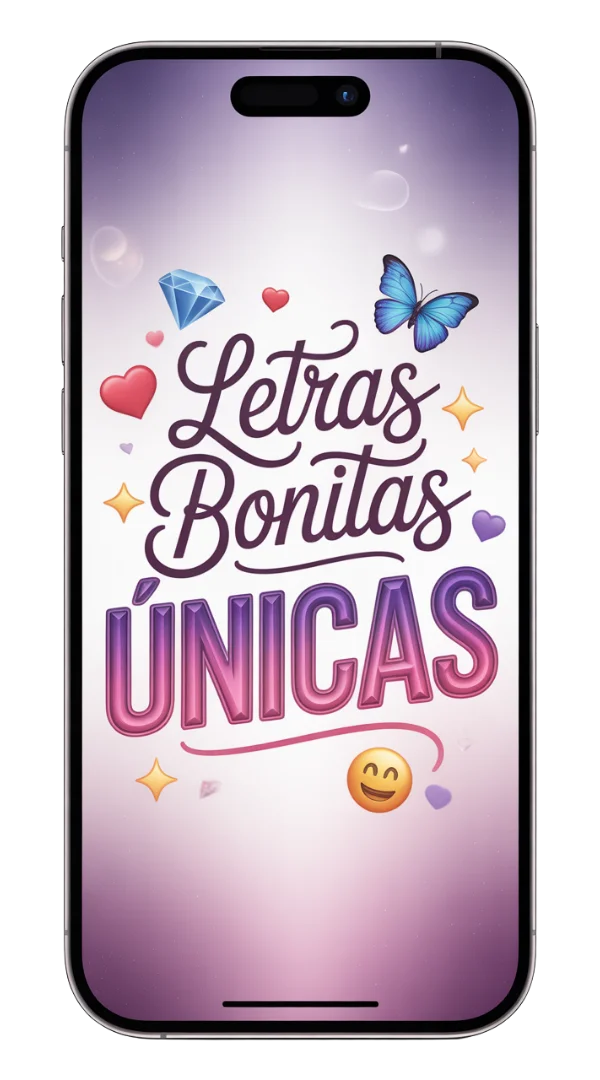
Texto Elegante
Un tipo de letras elegante transmite sobriedad y buen gusto. Entre los diferentes tipos de letras, este estilo es ideal para mensajes formales o presentaciones personales. Su apariencia limpia y estilizada ayuda a comunicar seriedad sin perder atractivo visual, siendo una opción muy valorada en contextos digitales profesionales.
Letras Cuadradas
El tipo de letras cuadrado se caracteriza por formas firmes y definidas. Muchos usuarios buscan tipo de letras diferentes para lograr un aspecto moderno y estructurado. Este estilo transmite orden y fuerza visual, lo que lo hace perfecto para títulos, nombres cortos o mensajes que necesitan impacto inmediato.
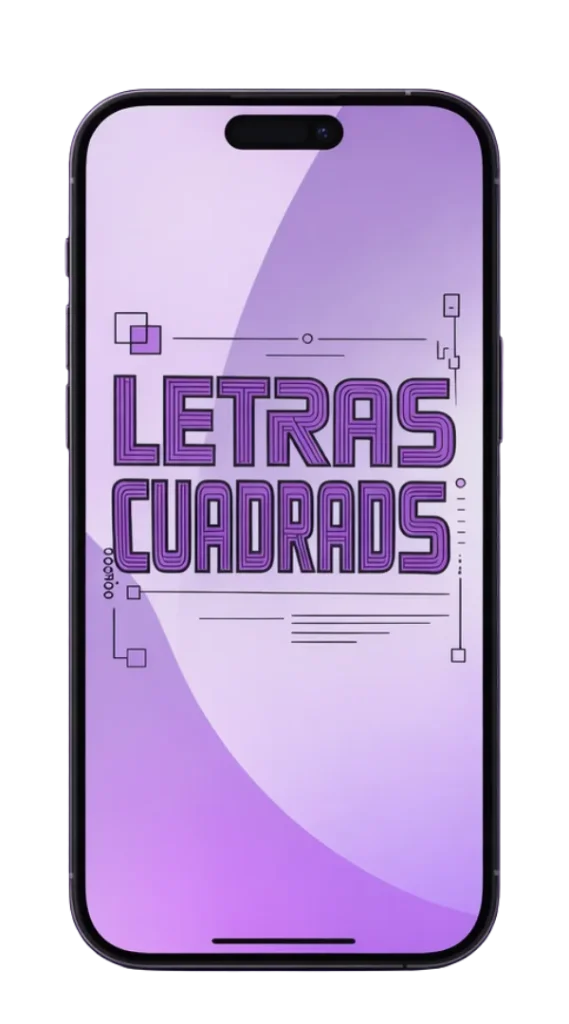
Escribe o pega tu texto
En el primer cuadro, introduce el texto que deseas transformar. Puedes escribir una palabra, una frase o un nombre completo.
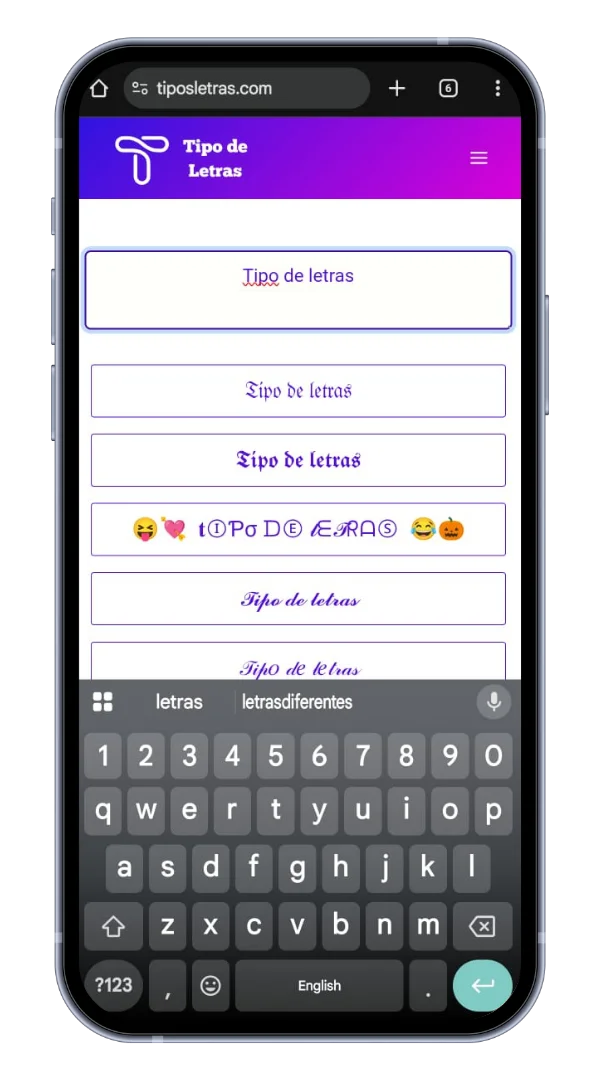
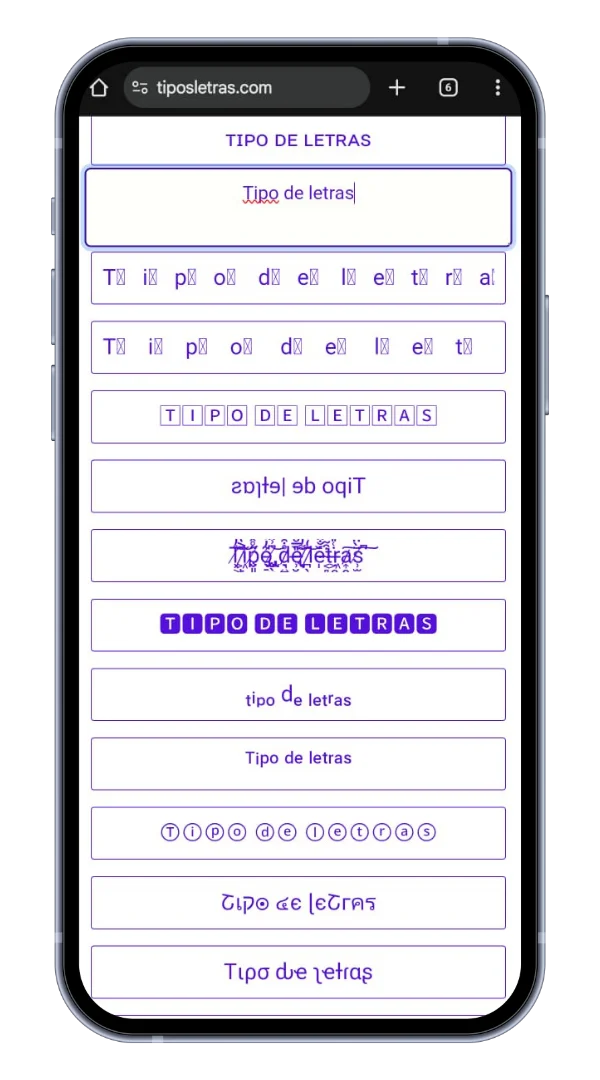
Visualiza los estilos automáticamente
Justo debajo, aparecerá la vista previa del texto convertida en distintos estilos de letras. No necesitas hacer clic en ningún botón, los cambios se generan de forma automática.
Explora los diferentes estilos disponibles
Desplázate hacia abajo para ver todas las variaciones de letras. Cada fila muestra un estilo distinto para que puedas elegir el que más te guste.
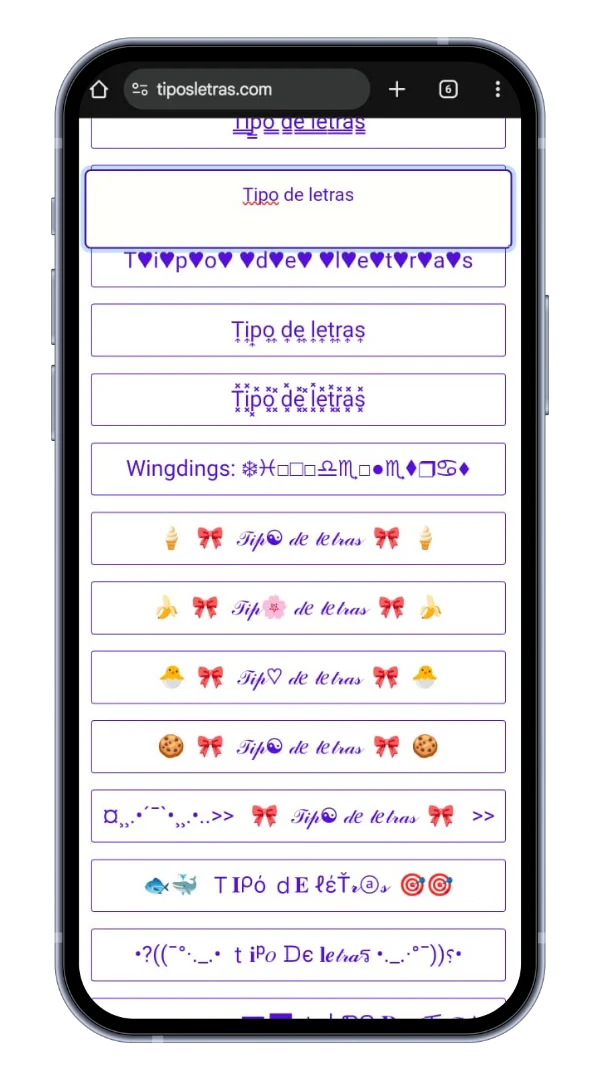
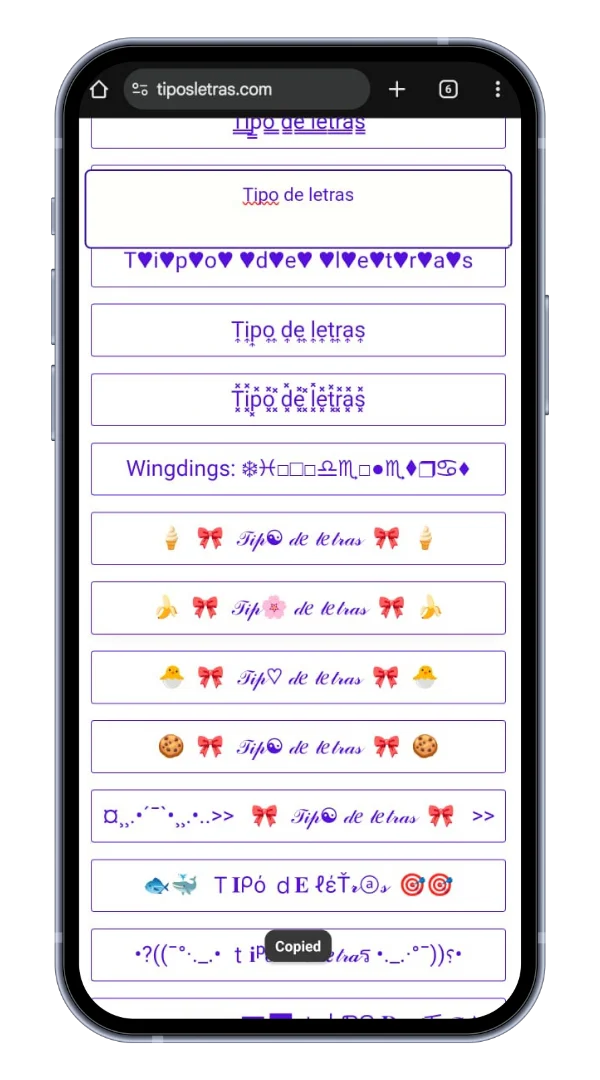
Copia el estilo que prefieras
Copia el resultado y úsalo donde quieras, gracias a la función de tipos de letras copiar y pegar.
Pega tu texto donde quieras
Puedes pegar el texto copiado en redes sociales, mensajes, perfiles, biografías o cualquier plataforma compatible.
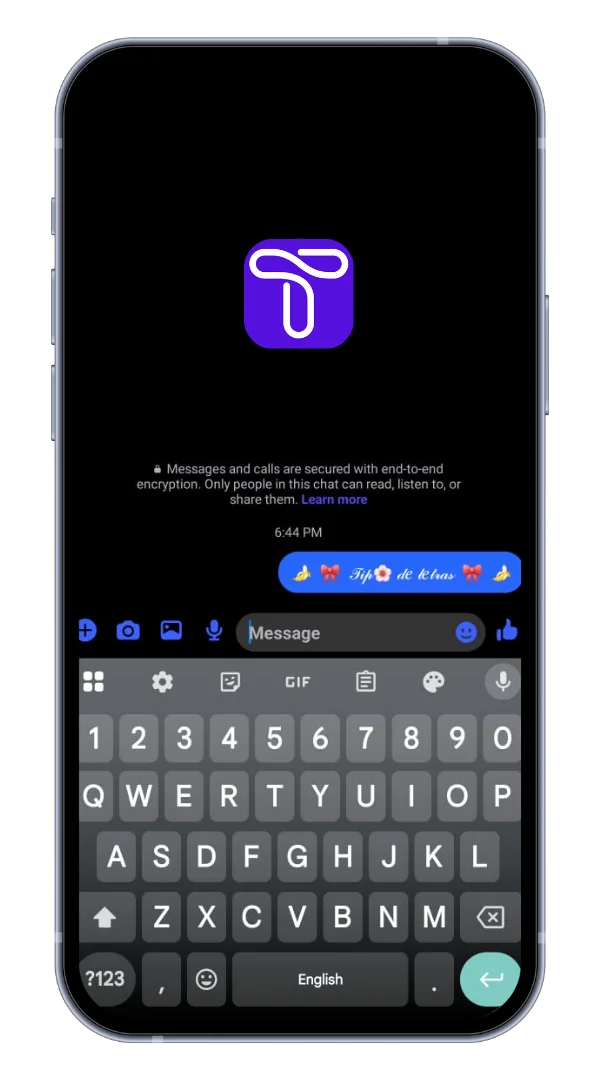
En solo segundos tendrás tu texto listo para usar en cualquier plataforma.
Tipos de estilos de fuente generados por Tipos De Letras
Conclusión
El uso creativo del texto se ha convertido en una forma moderna de expresión digital. Elegir el estilo adecuado permite destacar mensajes, transmitir emociones y reforzar la identidad personal en distintos espacios en línea. Con tantas opciones disponibles, experimentar con nuevas formas de escritura es sencillo, accesible y útil para cualquier persona que quiera darle un toque único a sus palabras. Además, si también te interesa mejorar tu experiencia en juegos, puedes consultar un MM2 trade checker para verificar el valor de los intercambios y tomar decisiones más informadas.